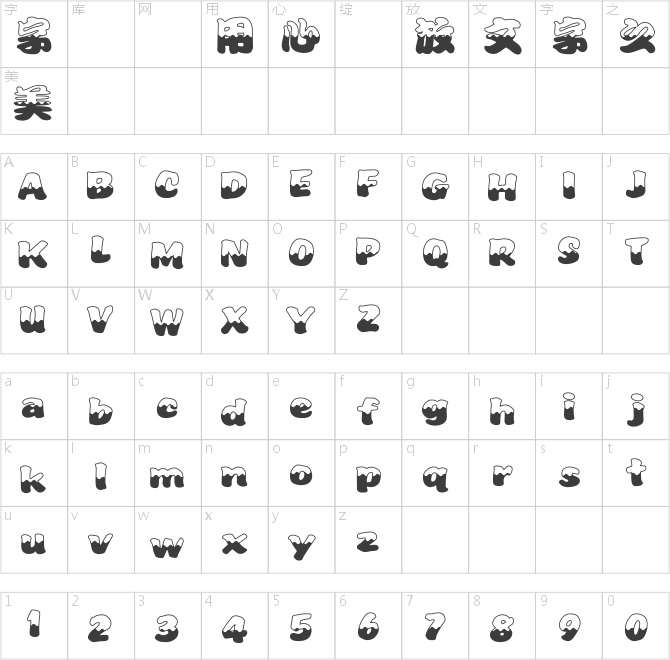
字體名稱(chēng): 王漢宗勘亭流一
王漢宗勘亭流一隨波字體字庫(kù)是一款讓人賞心悅目、百看不厭的中文字體,適合各類(lèi)廣告和產(chǎn)品包裝設(shè)計(jì)應(yīng)用,字體大小8.65MB,格式為ttf字體,上傳用戶(hù)是速拓科技,作者/版權(quán)方為王漢宗